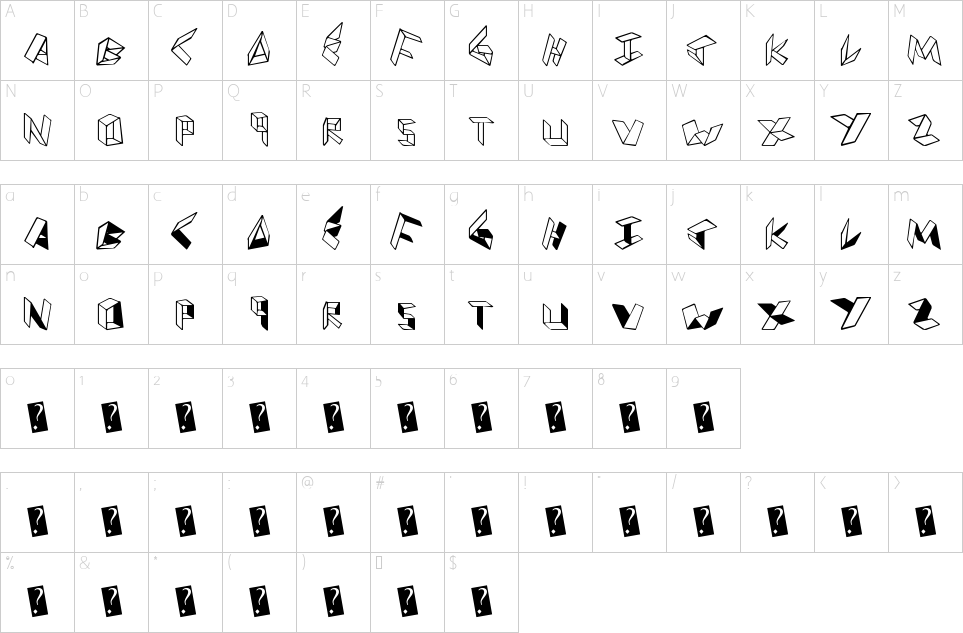
Descubra a beleza da fonte Paper Folder para seu próximo projeto gráfico com uma aparência elegante e natural. Esta fonte foi projetada por Xerographer Fonts e é perfeita para criar design gráfico agradável e elegante, especialmente para elementos que exijam um toque de sofisticação. Com um design minimalista e limpo, Paper Folder combina perfeitamente com diferentes estilos de design, como design de revistas, publicidade e criação de logos. Se você está à procura de uma fonte que não só oferece uma experiência de uso agradável, mas também adere ao conceito de design sustentável, Paper Folder é um ótimo escolha. Baixe a Paper Folder para Windows e Mac e experimente a diversão de criar um design com esta fonte incrivelmente agradável e versátil.